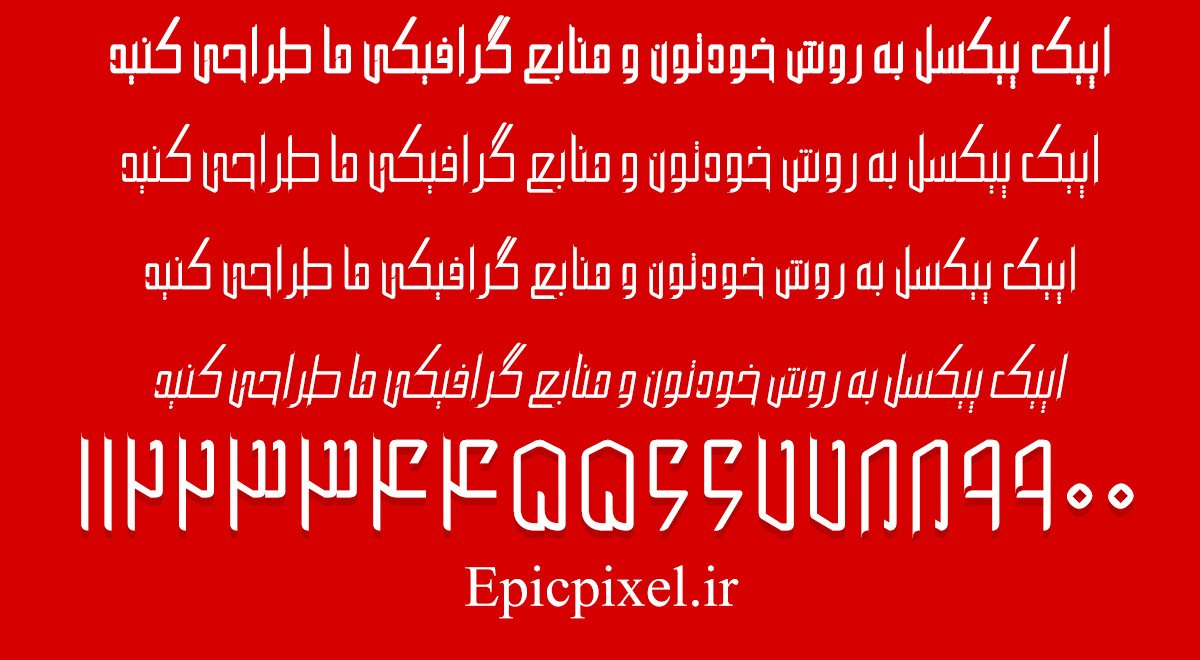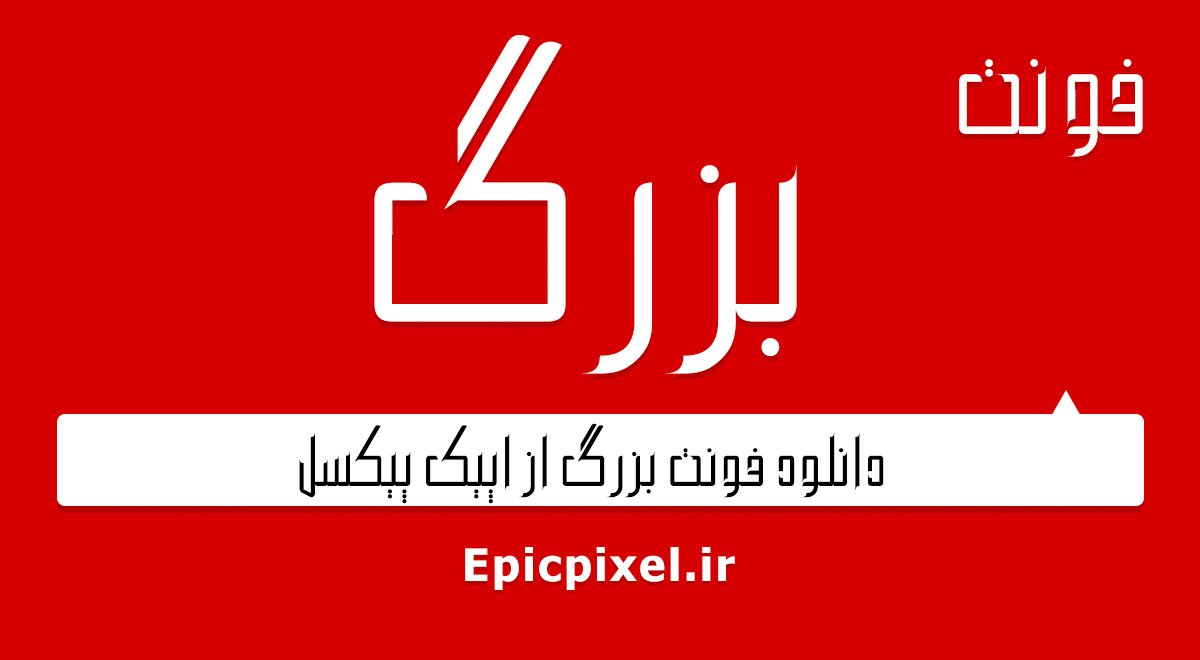
فونت بزرگ فارسی
دانلود رایگان فونت بزرگ ، درشت فارسی با اسم لاتین Mj Large . فونتهای درشت و لارج فارسی خوانایی متن را آسانتر میکند که این فونت بهترین انتخاب برای خوانایی بهتر است |
جذابیت خواندن با فونتهای درشت دانلود رایگان فونت فارسی بزرگ Large
چشم انسان در طول روز اطلاعات زیادی را پردازش میکند. گاهی خواندن متون ریز، مخصوصا روی صفحه نمایش، میتواند خستهکننده و حتی آزاردهنده باشد. راهحل چیست؟ استفاده از فونتهای درشت فارسی! این فونتها با خوانایی بالا، به چشمان شما در هنگام مطالعهی طولانیمدت استراحت میدهند. در این مقاله، به معرفی فونتهای درشت فارسی و نحوهی دانلود رایگان آنها میپردازیم.
چرا از فونت درشت فارسی استفاده کنیم؟
دلایل متعددی برای استفاده از فونت درشت فارسی وجود دارد. در اینجا به برخی از مهمترین آنها اشاره میکنیم:
- خوانایی بهتر: فونتهای درشت خواندن متن را برای همه، به ویژه افراد با مشکلات بینایی یا افرادی که از عینک استفاده نمیکنند، آسانتر میکند.
- کاهش خستگی چشم: با استفاده از فونت درشت، فشار کمتری به چشم وارد میشود و در نتیجه، خستگی چشم در هنگام مطالعهی طولانیمدت کاهش مییابد.
- جذب مخاطب: فونت درشت در طراحیهای گرافیکی و وبسایتها، توجه مخاطب را به خود جلب میکند و خواندن پیام اصلی را برای او آسانتر میسازد.
- مناسب برای افراد کمتوان: فونت درشت برای افراد دارای اختلالات یادگیری مانند डिスレکسی (dyslexia) یا افرادی که به تازگی سوادآموزی را فراگرفتهاند، بسیار مفید است.
دانلودانواع فونت درشت فارسی
طراحان خوشبختانه فونتهای درشت متنوعی را با سبکهای مختلف برای مصارف گوناگون طراحی کردهاند. برخی از محبوبترین انواع فونت درشت فارسی عبارتند از:
- فونتهای تحریری این فونتها شبیه نوشتههای دستنویس هستند و حس صمیمیت و راحتی را القا میکنند.
- فونتهای فانتزی این فونتها با طراحیهای غیرمعمول و خلاقانه، توجه مخاطب را جلب میکنند و برای طراحیهای گرافیکی و سرگرمکننده مناسب هستند.
- فونتهای بدون سَریف (Sans-Serif) این فونتها برای خواندن روی صفحه نمایش و در اندازههای درشت، ایدهآل هستند.
- فونتهای با سَریف (Serif) این فونتها با ظاهری رسمیتر، برای متنهای طولانی و اسناد چاپی مناسبترند.
نمونههایی از کاربرد فونت درشت فارسی:
- طراحی پوستر و تراکت: فونتهای درشت برای جلب توجه مخاطب در طراحیهای گرافیکی مانند پوستر و تراکت بسیار مناسب هستند.
- طراحی وبسایت: با استفاده از فونت درشت در وبسایت، خوانایی محتوا برای کاربران آسانتر میشود و تجربهی کاربری بهتری را رقم میزند.
- کتابهای الکترونیکی: استفاده از فونت درشت در کتابهای الکترونیکی، خواندن متن را برای افراد با مشکلات بینایی آسانتر میکند.
- ارائههای پاورپوینت: با استفاده از فونت درشت در ارائههای پاورپوینت، محتوای ارائه برای مخاطبان واضحتر و قابلفهمتر خواهد بود.
1. چه تفاوتی بین فونت درشت و فونت بزرگ وجود دارد؟
فونت درشت به فونتی گفته میشود که خوانایی آن در اندازههای بزرگ آسان باشد. فونت بزرگ به فونتی گفته میشود که صرفا اندازهی آن بزرگ است، اما خوانایی آن در اندازههای بزرگ ممکن است آسان نباشد.
2. آیا فونتهای درشت فارسی برای افراد کمتوان مفید هستند؟
بله، فونتهای درشت فارسی برای افراد کمتوان مانند افراد دارای مشکلات بینایی یا اختلالات یادگیری بسیار مفید هستند.
4. بهترین وبسایت برای دانلود فونت درشت فارسی کدام است؟
وبسایتهای مختلفی برای دانلود فونت درشت فارسی وجود دارد. برخی از محبوبترین این وبسایتها عبارتند از فونتیاب، اپیک پیکسل.
کلام آخر
استفاده از فونتهای درشت فارسی، خوانایی متن را برای همه آسانتر میکند و تجربهی کاربری بهتری را رقم میزند. با دانلود رایگان فونتهای درشت فارسی از وبسایتهای معتبر، میتوانید از مزایای این فونتها در طراحیهای گرافیکی، وبسایت، کتابهای الکترونیکی و ارائههای خود بهرهمند شوید.
چقدر خوبه چون معمولا فونت بزرگ داشتیم ولی همه تو پر بودند اما این در عین نازکی که داره بزرگ هم هست و این خیلی عالیه